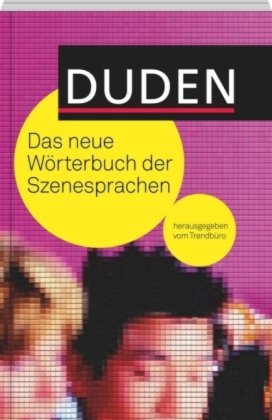
Duden: Neues Wörterbuch der Szenesprachen
habe diesen Duden nicht vorliegen, und die Samples sind grausig. Deswegen hat auch whatthe und identi nix gehülft.
Sans Serif
zweigeschossiges a mit *recht* großer Punze
dreigeschossiges g
l mit Schwänzerl
recht "geschlossenes" s
...dachte das grenzt die Auswahl ganz schön ein. Wohl nicht. Ohne euch komme ich jedenfalls nicht weiter!
Hier ein weiteres Bild …
Das sieht doch prima aus. Ich meine aber dass das "c" der Akkurat ein ganz klein wenig weniger weit geöffnet ist. Aber das mag auch täuschen …
Ich meine aber dass das "c" der Akkurat ein ganz klein wenig weniger weit geöffnet ist.
Empfinde ich auch so - dennoch ist die akkurat für meinen Geschmack auf jeden Fall nah genug dran!